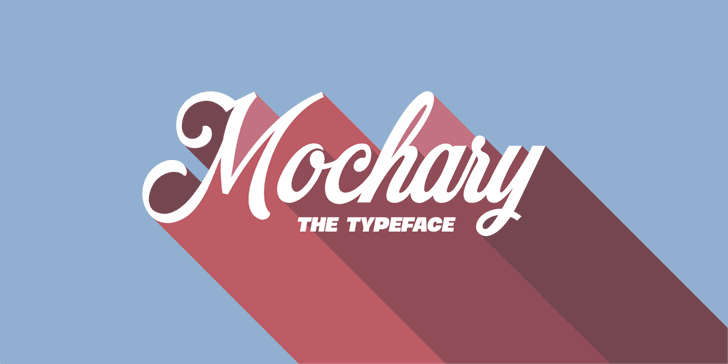
Mochary Font – Fonte Grátis
Mochary Font
A fonte “Mochary” foi criada pelo designer Hamilton para capturar a essência da escrita por trás do papel mochila tradicional brasileira. Especialmente perfeita para adicionar um toque cultural e autêntico aos projetos de design gráfico, sua caligrafia exibida destaca-se em qualquer tipo de projeto. Perfeita tanto para aplicativos digitais quanto para impressões a preto e branco ou coloridas, “Mochary” oferece uma gama de opções desde linhas sutilmente traçadas até texturas mais densas e detalhadas que se adaptam perfeitamente ao design. Ideal para designers gráficos interessados em incorporar um elemento visual único à sua arte digital ou impressão, “Mochary” é uma fonte caligráfica perfeita para projetos de design profissional. Visite a página do designer para adquirir uma licença comercial.